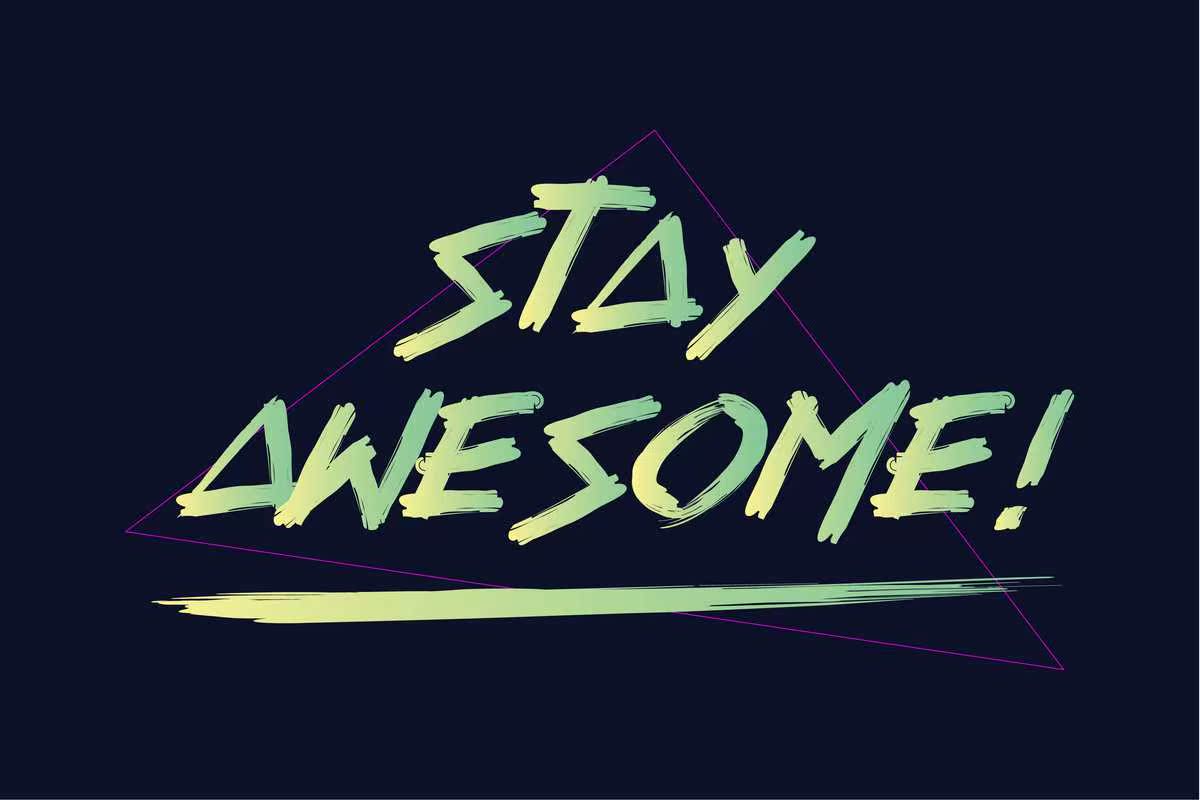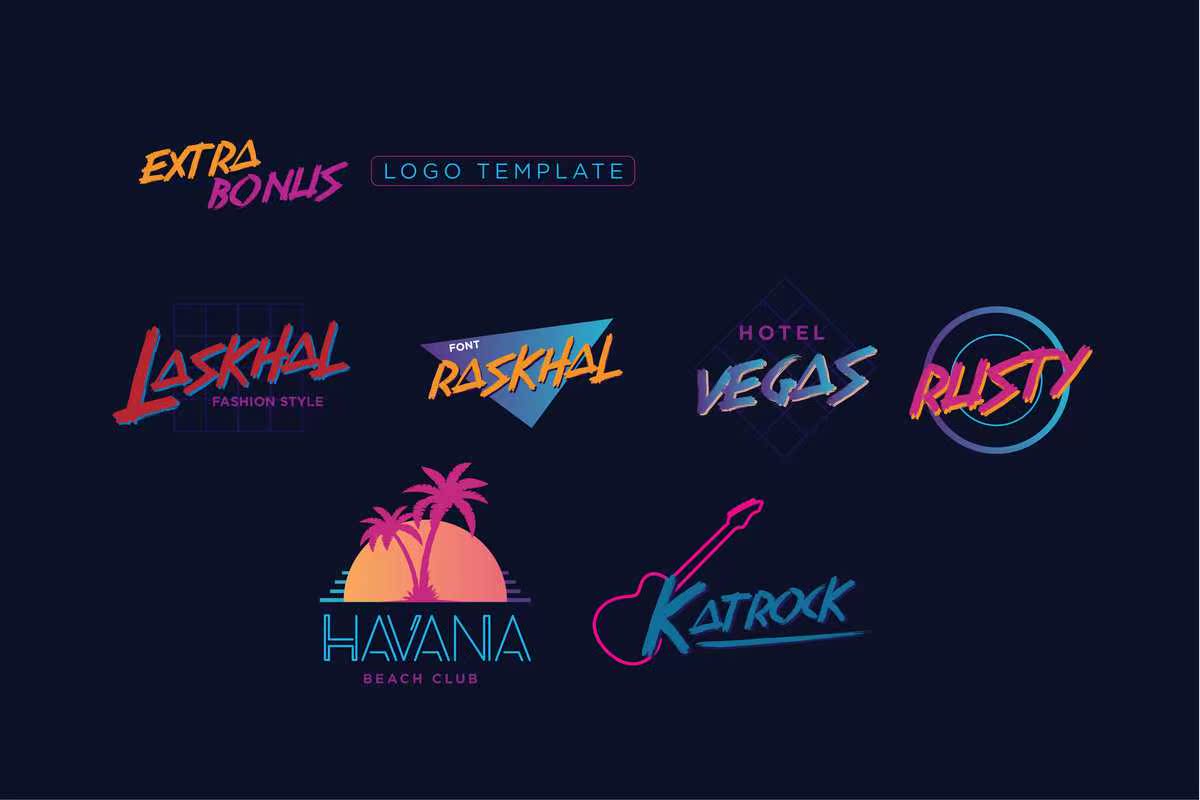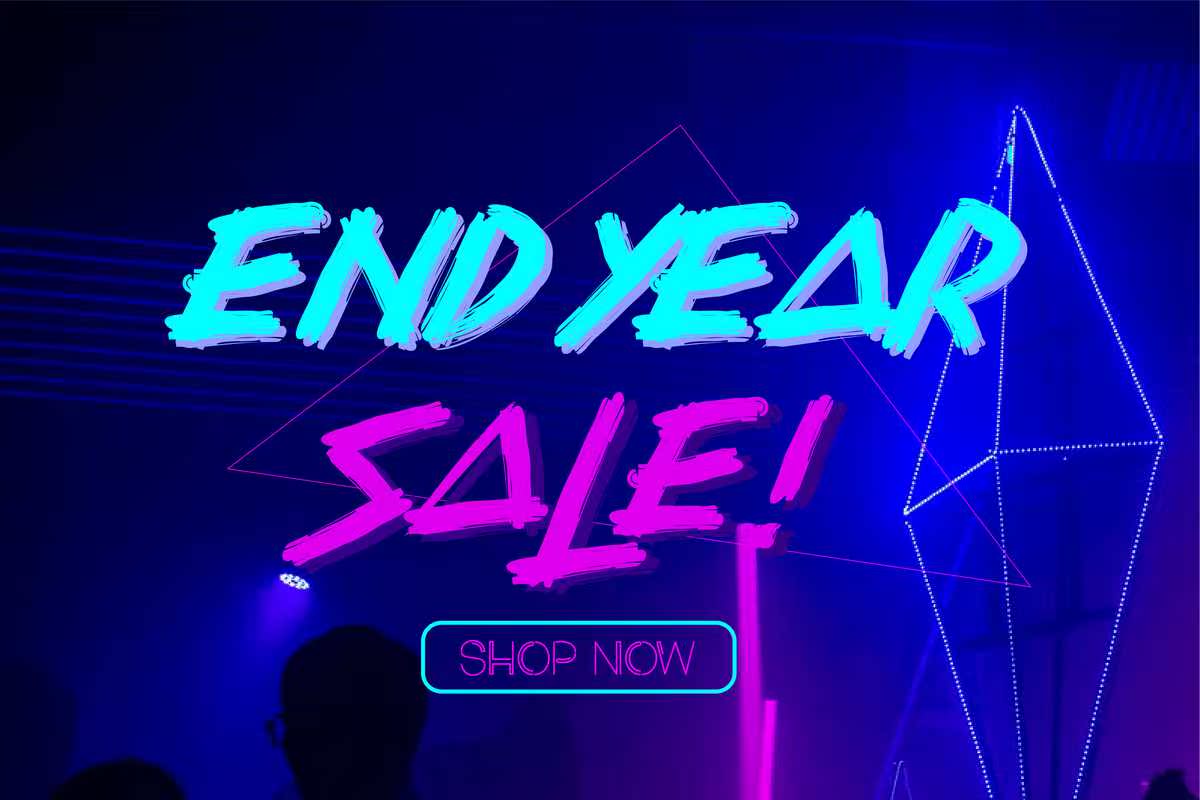
Raskhal受到1980年和Neonlights的启发。Raskhal为设计项目的多样性提供了美丽的平面协调,包括徽标和品牌、社会媒体、广告和产品设计。Raskhal受到1980年和Neonlights的启发。Raskhal为设计项目的多样性提供了美丽的平面协调,包括徽标和品牌、社会媒体、,广告和产品设计